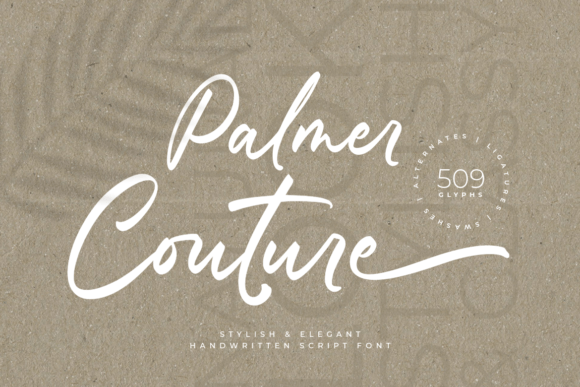
Palmer Couture
Palmer Coutureのような高品質の素材をお探しの場合、このプレミアムパッケージはクリエイティブなプロジェクトに素晴らしい選択です。
POD(オンデマンド印刷)製品、結婚式の招待状、またはソーシャルメディアのグラフィックを作成している場合でも、Palmer Coutureは理想的です。